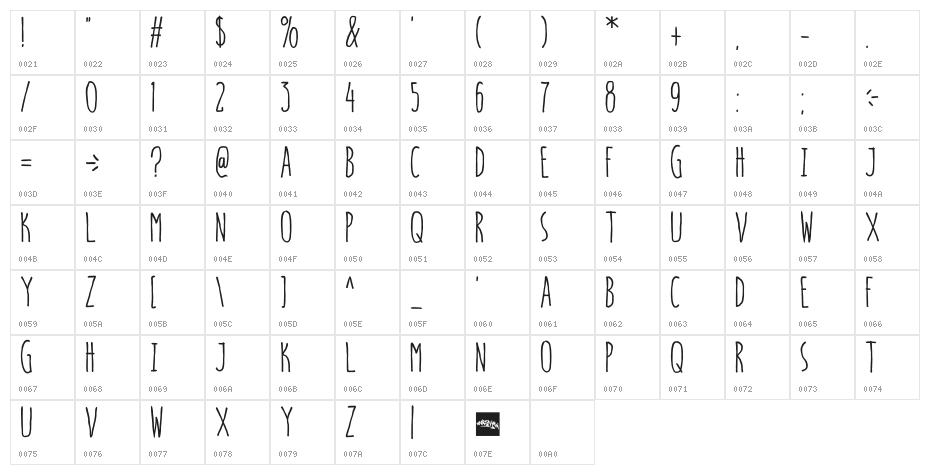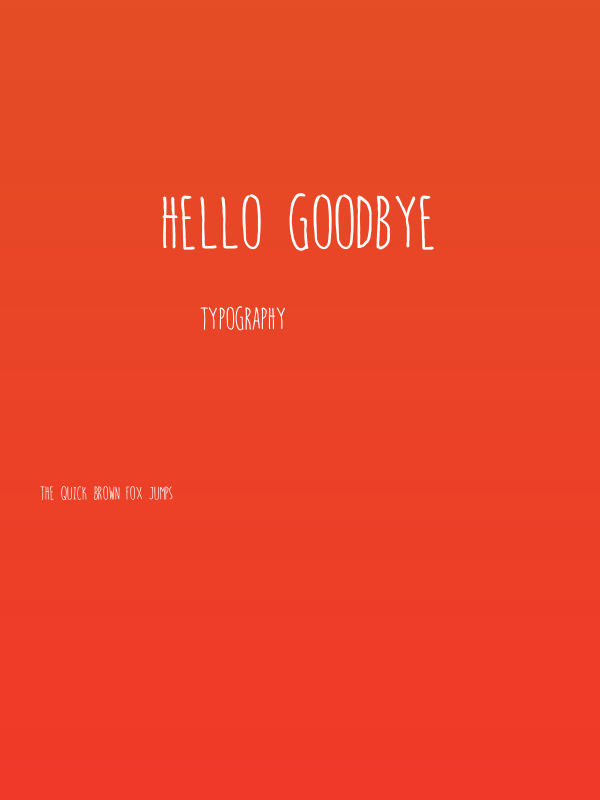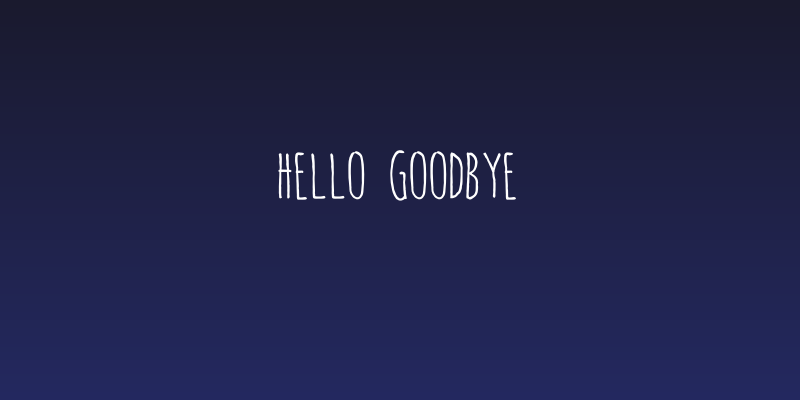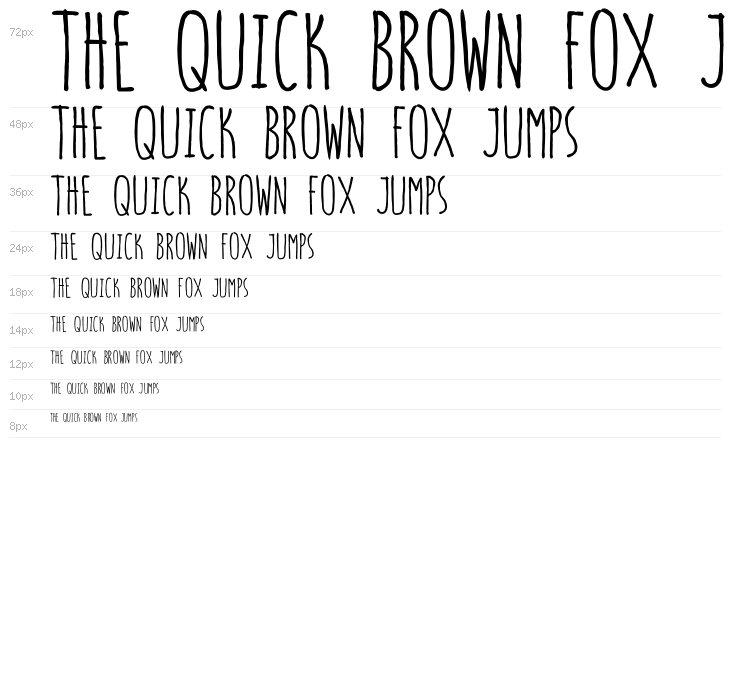
hello goodbye Font
| Estilo general | Casual |
| Caso de uso | Headlines, Logos, Informal Text |
| Proyectos propuestos | Ideal for greeting cards, children's books, playful branding, and casual invitations. |